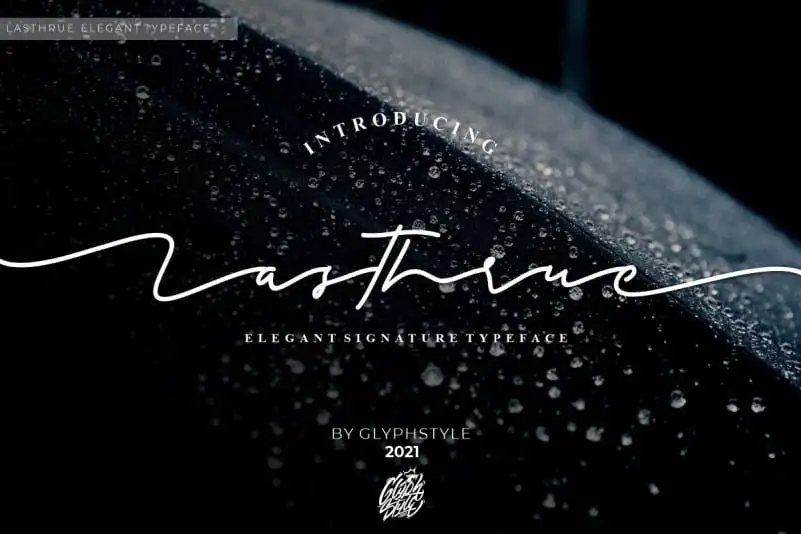
Lasthrue Signature Script Font – Download Grátis
A Lasthrue Signature Script Font é uma opção perfeita para quem busca uma fonte cuidadosamente detalhada, com linhas monolineas e curvas naturais. Este design elegante e encantador está pronto para enriquecer qualquer projeto que exija um toque sofisticado, desde assinaturas de casamento até logotipos de marca ou embalagens de produtos. Além disso, sua versatilidade faz dela uma escolha ótima tanto para eventos formais quanto para aplicativos digitais, como cards de business e logo de negócios. Essa fonte é o toque final que você precisa para dar vida ao seu design mais sofisticado.